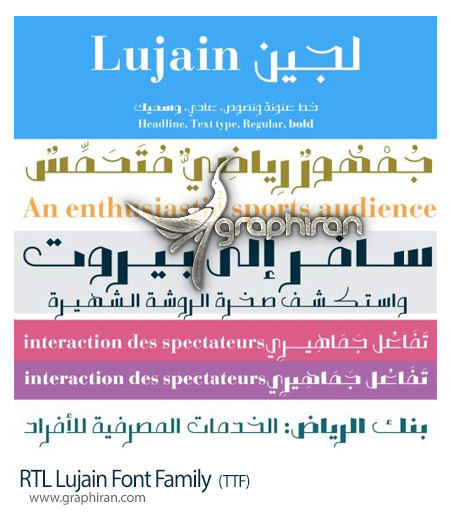
دانلود فونت عربی لجین RTL Lujan Font Family یک فونت خلاقانه عربی دارای ضخامت های مختلف مناسب برای طراحی وب، طراحی تبلیغاتی و انواع پروژه های گرافیکی می باشد. این فونت فانتزی عربی را می توانید از گرافیران دانلود کرده و در طرح های گرافیکی خود استفاده کنید.